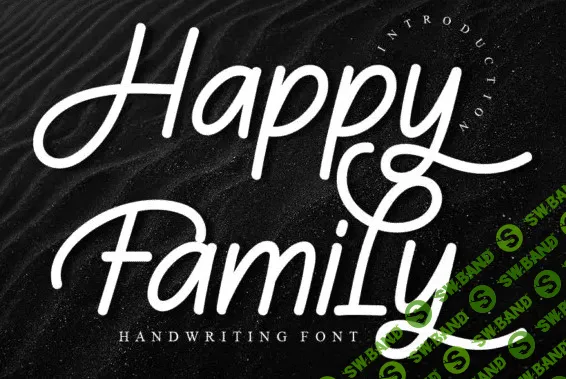
Название: Happy Family Font
Создавайте великолепные и вневременные дизайны с помощью Happy Family, интересного и уникального рукописного шрифта.
Влюбитесь в его невероятно стильный внешний вид и используйте его для логотипов, цитат, приглашений, визитных карточек, презентаций powerpoint и многого другого!